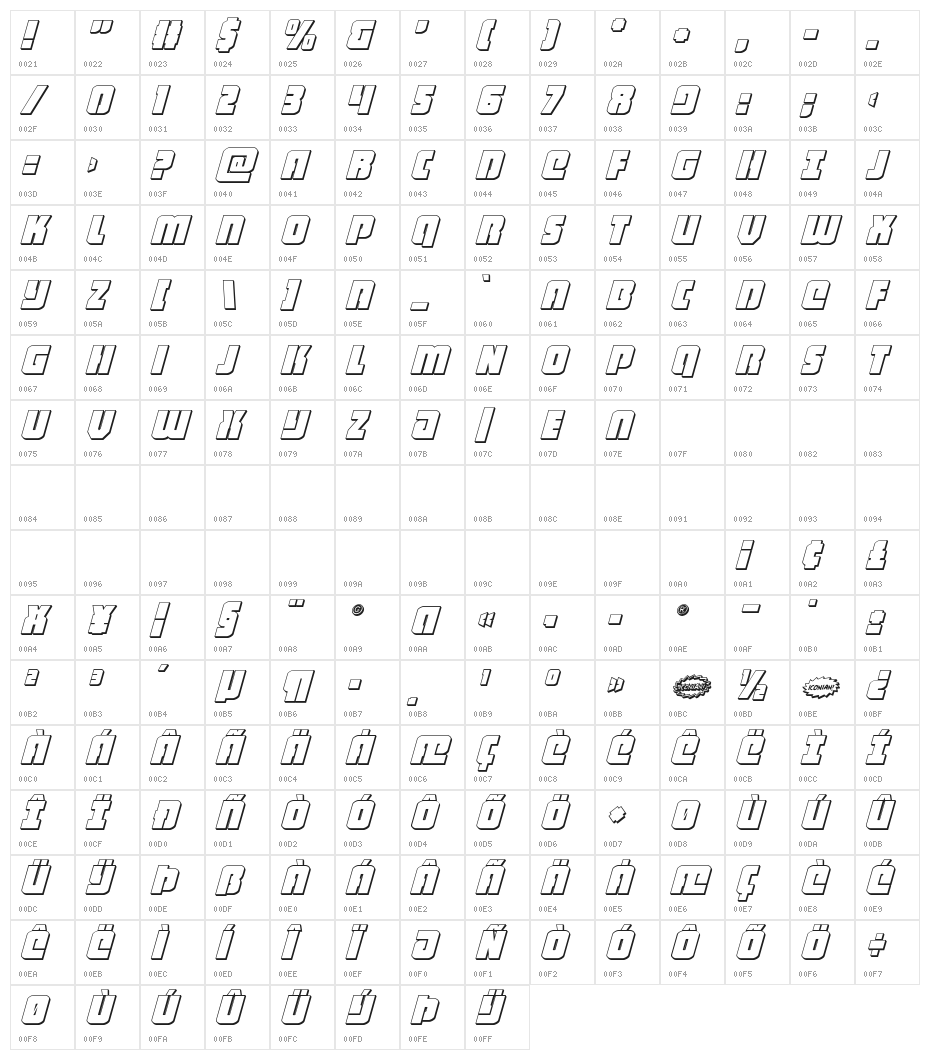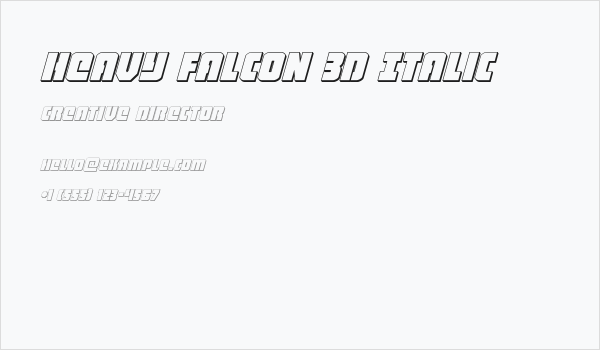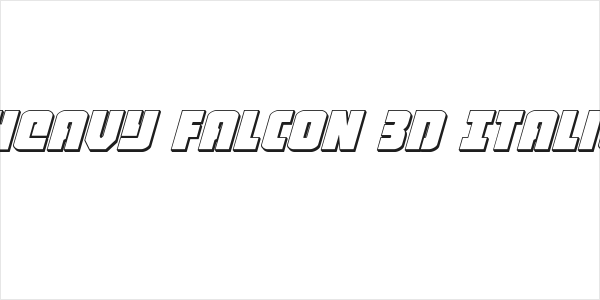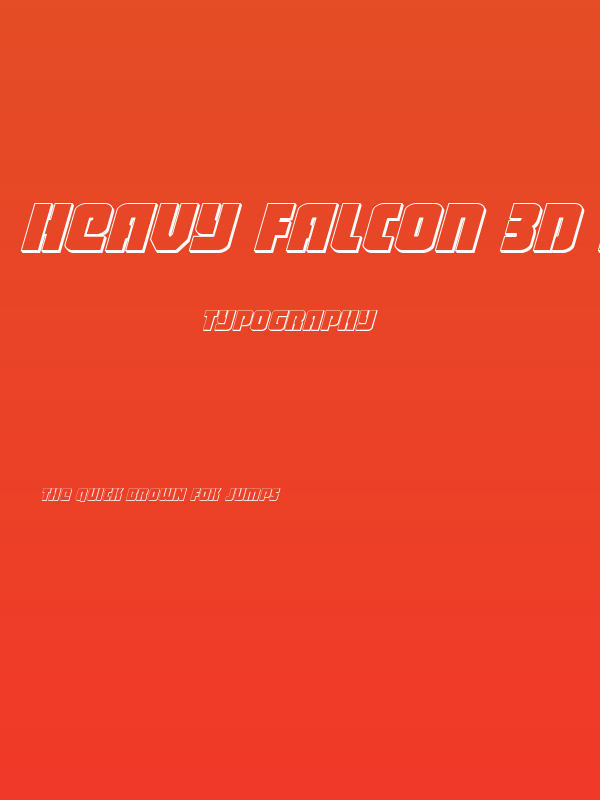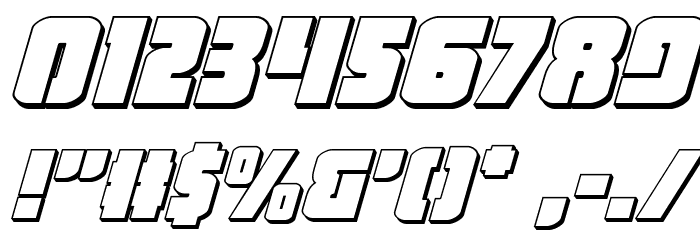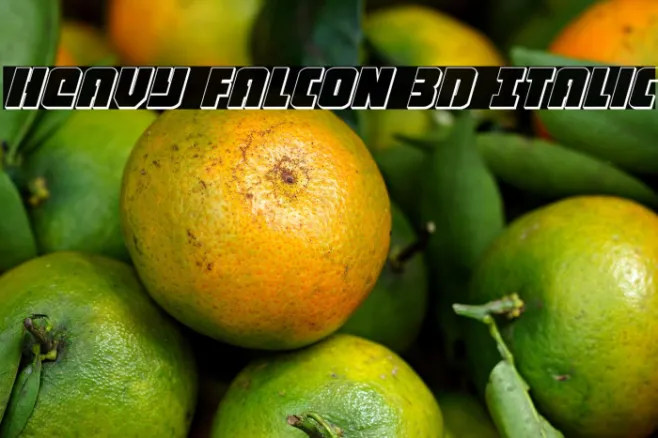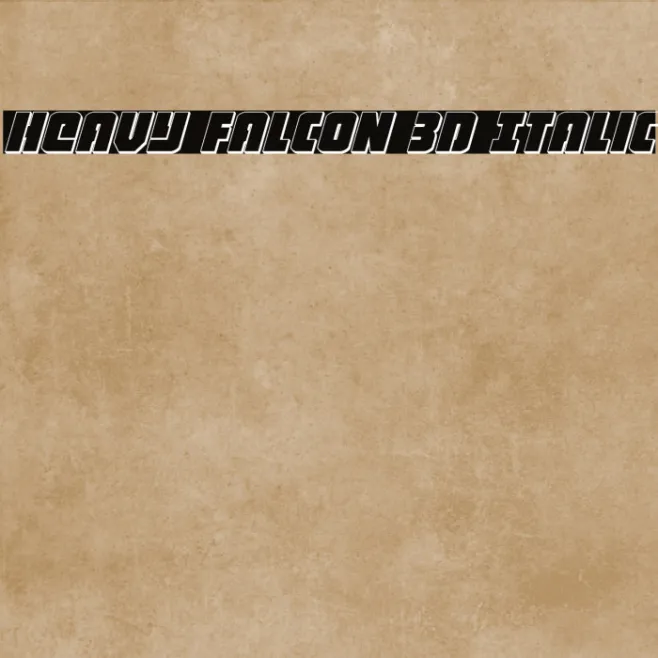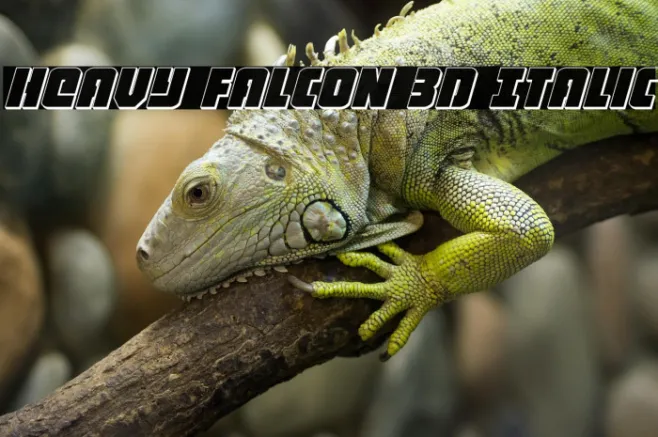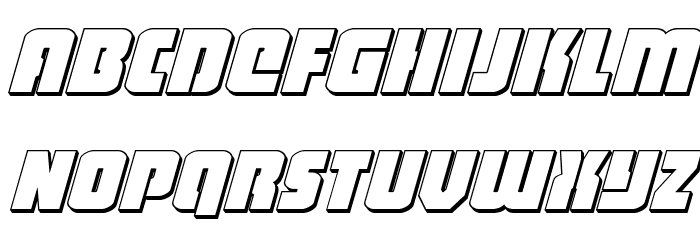
Heavy Falcon 3D Italic Font
| Projets proposés | Ideal for video game titles, sci-fi movie posters, technology branding, and any project needing a modern, standout typeface. |